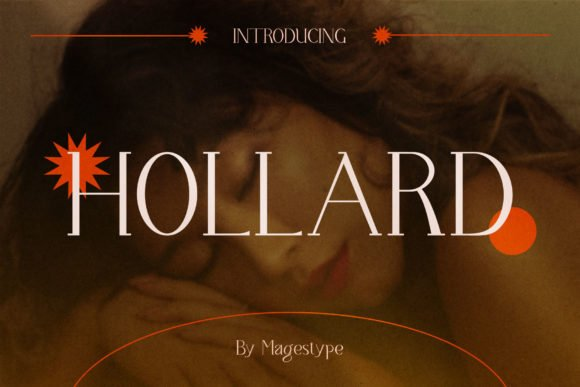
Название: Holllard Font (2021)
Holllard - это высокий, модный и современный шрифт с засечками.
Влюбитесь в его элегантный стиль и используйте его для создания великолепных свадебных приглашений, красивых канцелярских принадлежностей, привлекательных постов в социальных сетях и многого другого!
Название: Holllard Font (2021)
Holllard - это высокий, модный и современный шрифт с засечками.
Влюбитесь в его элегантный стиль и используйте его для создания великолепных свадебных приглашений, красивых канцелярских принадлежностей, привлекательных постов в социальных сетях и многого другого!